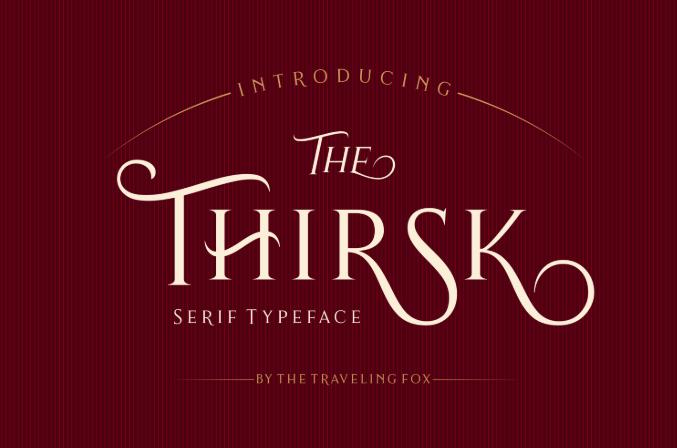
[Creativefabrica] Thirsk Font (The Traveling Fox)
Thirsk - это декоративный, винтажный шрифт с засечками. Шрифт Thirsk имеет множество альтернатив, что делает его очень универсальным, который можно использовать в самых разных проектах. Независимо от того, в каком проекте вы его используете, вы обязательно произведете впечатление.